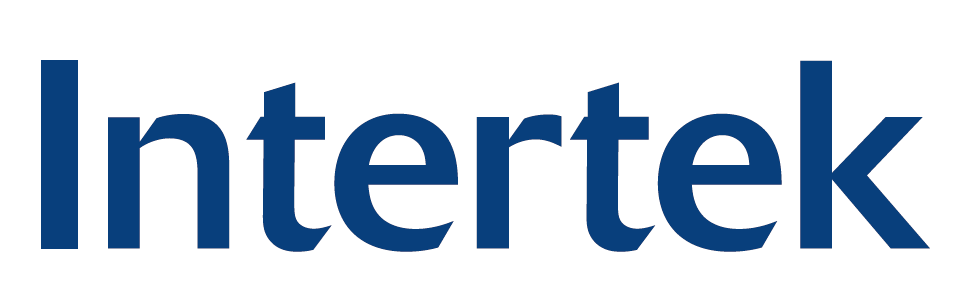
Hat jemand ne Idee, was das "Intertek" sein könnte?
Die üblichen Methoden (PDF, Whatthefont, ...) haben nichts gebracht.
Charakteristisch ist das "t", und sie kommt mir bekannt vor ...
Altuna geht in die Richtung …
Die Delta ist’s eher …
Wenn ich die Delta mit dem Logo vergleich, passt das schon perfekt.
Der Screenshot des Logos entstammt jenem pdf.